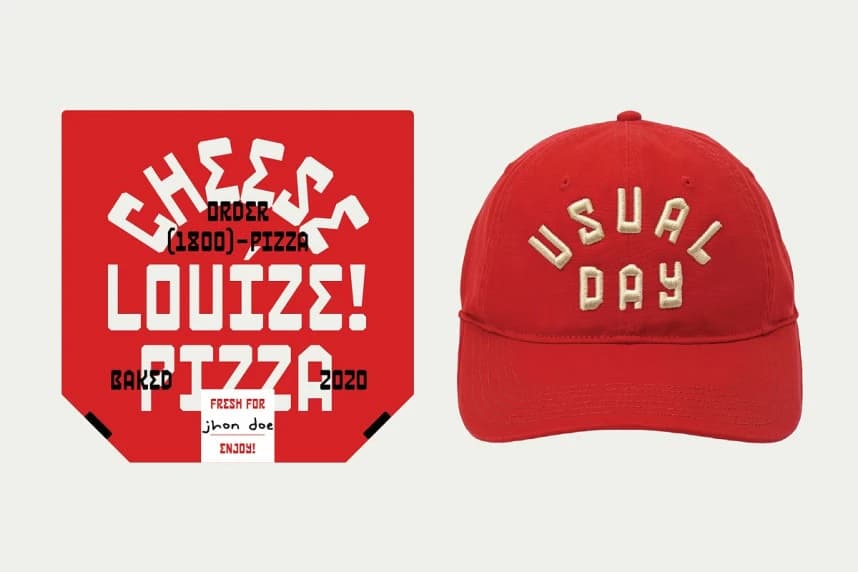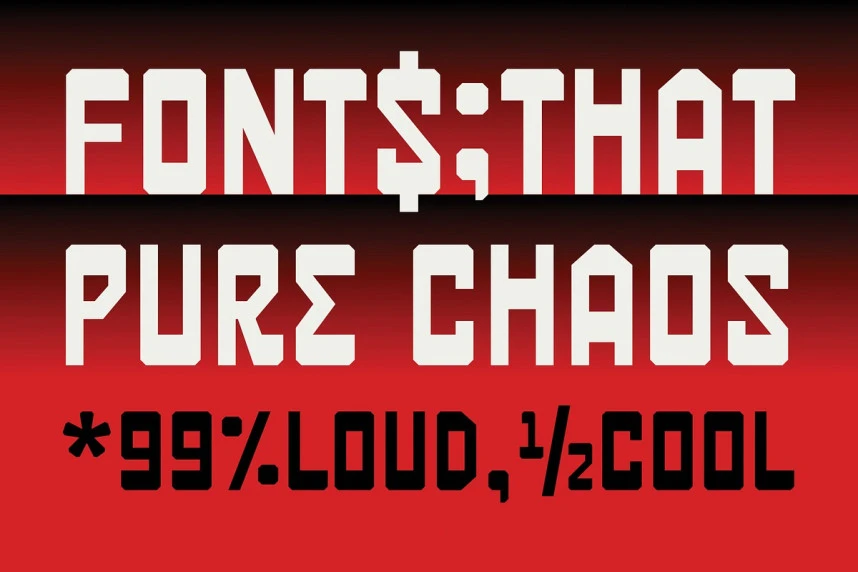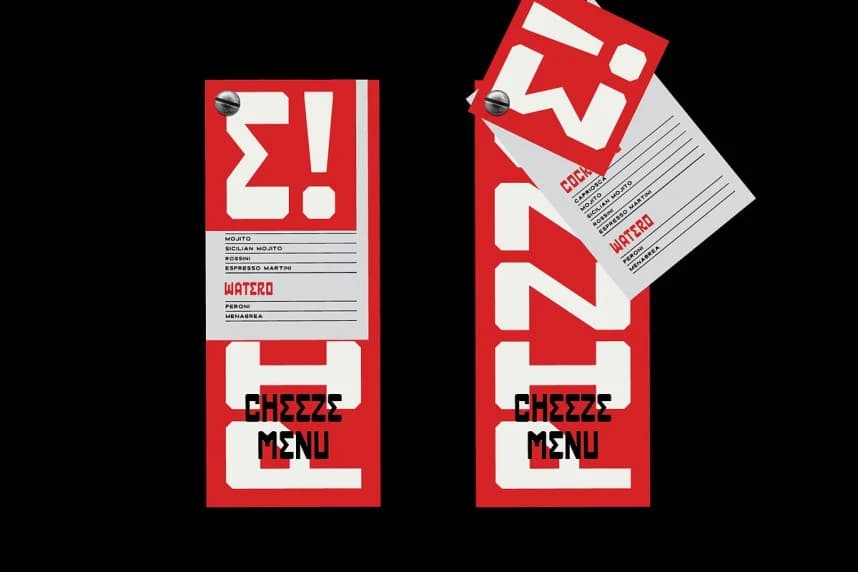
SFC Privet Font
SFC Privet Font, endüstriyel mimari, mekanik yapı ve modern brutalist estetiklerden ilham alan cesur geometrik bir gösterim yazı tipidir. Keskin açılı hatlar, kompakt oranlar ve kendinden emin bir kalınlık dağılımı ile tasarlanmıştır.
SFC Privet Font, endüstriyel mimari, mekanik yapı ve modern brutalist estetiğinden ilham alan cesur bir geometrik gösterim fontudur. Keskin köşeli kesimler, kompakt oranlar ve kendinden emin bir ağırlık dağılımıyla tasarlandı.